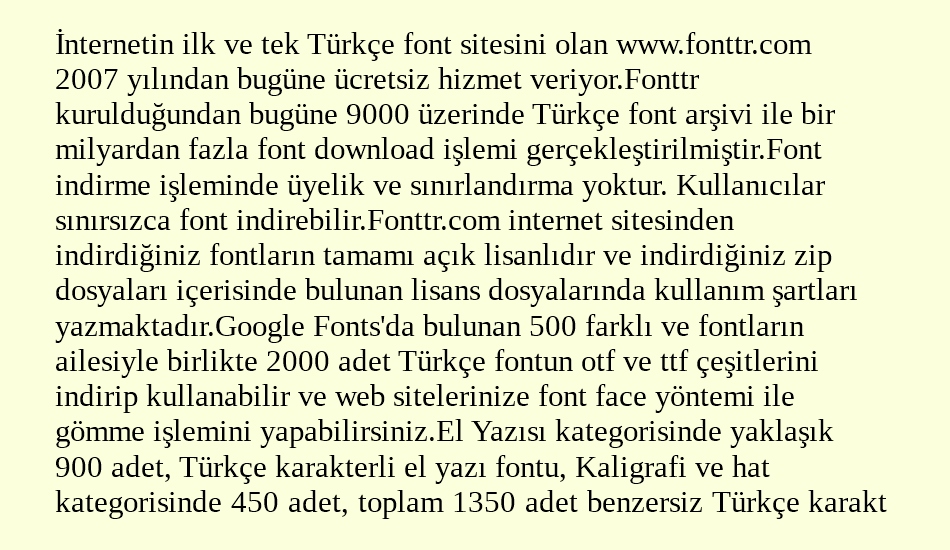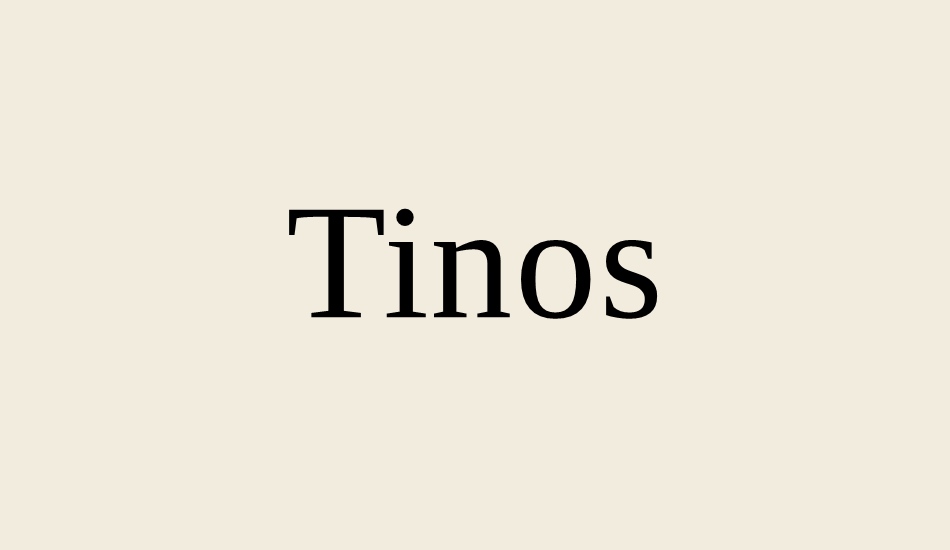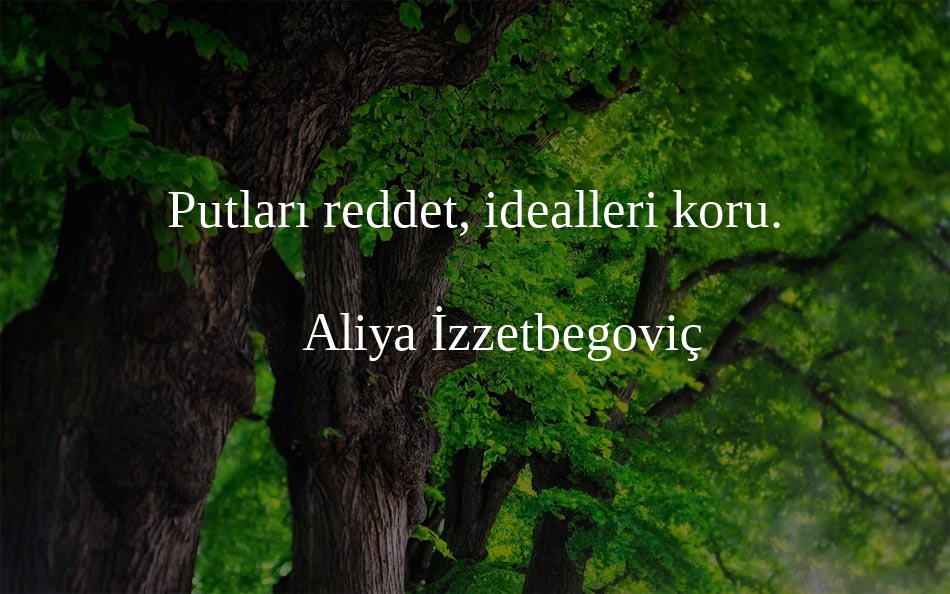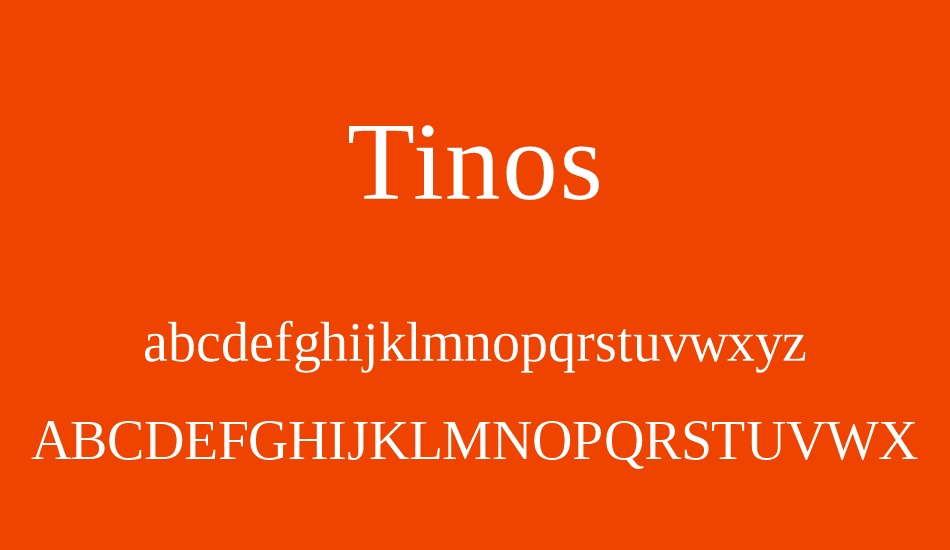
Tinos Font Family font
Tinos, Steve Matteson tarafından metrik olarak Times New Roman ™ ile uyumlu yenilikçi ve ferahlatıcı bir serif tasarımı olarak tasarlandı. Tinos font, ekranda okunabilirlik özellikleri ve Pan-European WGL karakter seti sunar ve platformlar arasında belge taşınabilirliğini ele alan genişlik uyumlu yazı tipleri arayan geliştiricilerin ihtiyaçlarını karşılar.
Tinos font